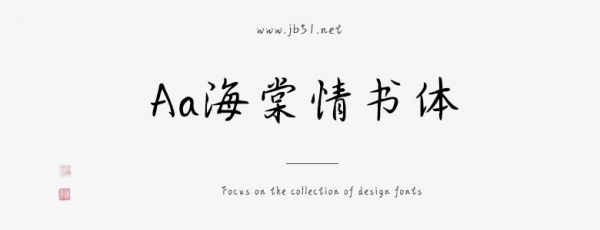
Aa海棠情書體是一款不錯的藝術(shù)字體,由Aa字庫出品,字體筆觸適中,書寫流暢,擁有字符數(shù)8029和字形數(shù)8009,具有很好的視覺感,適合應(yīng)用于藝術(shù)設(shè)計、平面宣傳設(shè)計、網(wǎng)頁設(shè)計,書法字帖等領(lǐng)域,需要的朋友可以前來本站下載。